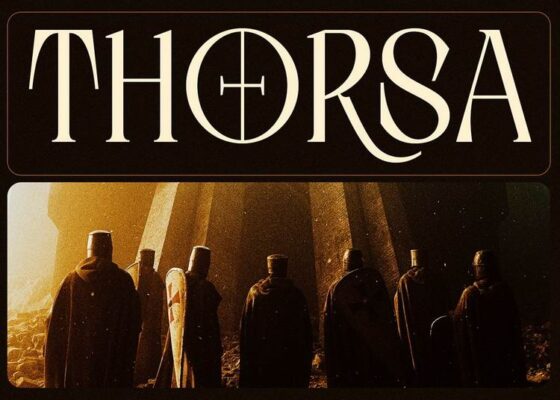
Thorsa ~ Free Font
Thorsa ~ Free Font | Thorsa ~ Бесплатный шрифт
Обзор шрифта: Thorsa ~ Бесплатный шрифт (Thorsa ~ Free Font)
✦ Thorsa is a unique serif typeface that stands out with its sharp and bold design, yet carries a deep meaning. Designed specifically to meet the needs of headlines, news posters, and other significant visual content, Thorsa captures attention with its distinctive style. The pointed and strong characteristics of this font give it a commanding presence, making it ideal for impactful and memorable headlines.
✦ Each letter in Thorsa is crafted with precision, ensuring clarity and readability while maintaining an artistic flair. This font not only serves the practical purpose of delivering information effectively but also adds a layer of sophistication and depth to any design it is used in.
✦ Whether for print or digital media, Thorsa enhances the aesthetic appeal and ensures that the message stands out prominently. Its versatility allows it to be used across various platforms and for different types of content, making it a valuable asset for designers and creators seeking to make a statement.
✦ Thoreau — это уникальный шрифт с засечками, который выделяется своим четким и смелым дизайном и в то же время несет в себе глубокий смысл. Разработанный специально для оформления заголовков, новостных постеров и другого значимого визуального контента, Thorsa привлекает внимание своим неповторимым стилем. Четкие и выразительные характеристики этого шрифта придают ему выразительный вид, что делает его идеальным для создания эффектных и запоминающихся заголовков.
✦ Каждая буква в Thorsa выполнена с особой точностью, что обеспечивает четкость и читабельность при сохранении художественного стиля. Этот шрифт не только служит практической цели эффективной передачи информации, но и придает изысканность и глубину любому дизайну, в котором он используется.
✦ Как для печатных, так и для цифровых носителей, Thorsa повышает эстетическую привлекательность и гарантирует, что сообщение будет выделяться на общем фоне. Его универсальность позволяет использовать его на различных платформах и для различных типов контента, что делает его ценным приобретением для дизайнеров и создателей, стремящихся заявить о себе.